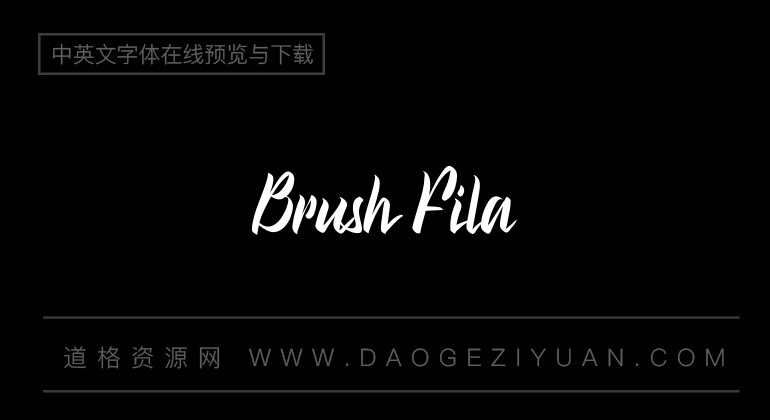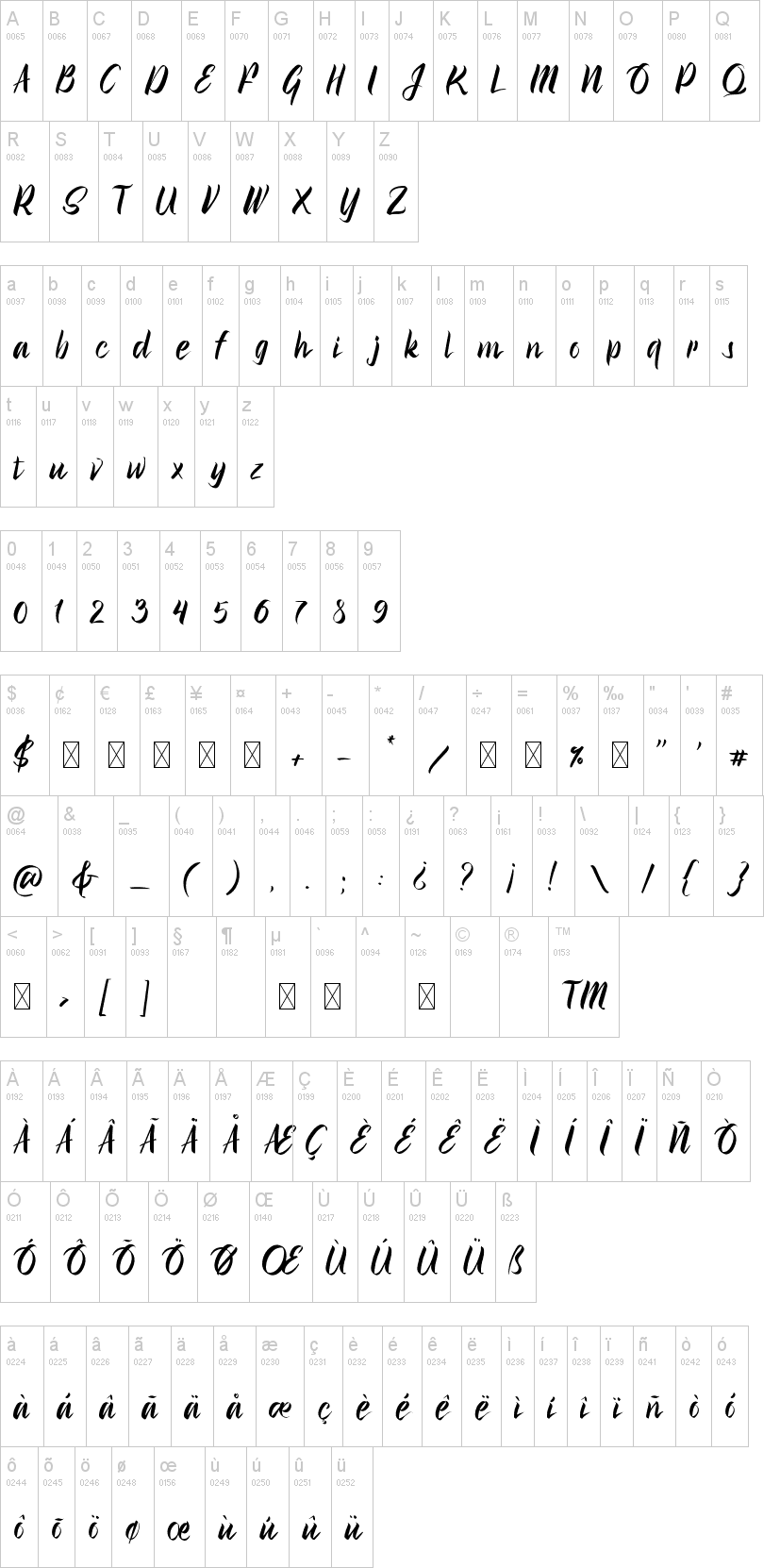
Brush Fila 是一种手写风格的字体,拥有粗犷、流畅、有机的感觉。它的笔画仿佛是由毛笔或油漆刷完成的,因此它非常适合用于印刷、广告、海报、标志等需要强调手写感觉的设计。Brush Fila 字体家族包括多个不同的字重和变体,可以适应不同的设计需求,是一款非常实用的字体。内容介绍
Brush Fila是一款非常不错的手写艺术字体,具有很好的视觉感,适合于文化类的宣传设计、商业类品牌的广告和产品包装设计以及个性化文字排版等较多场景。